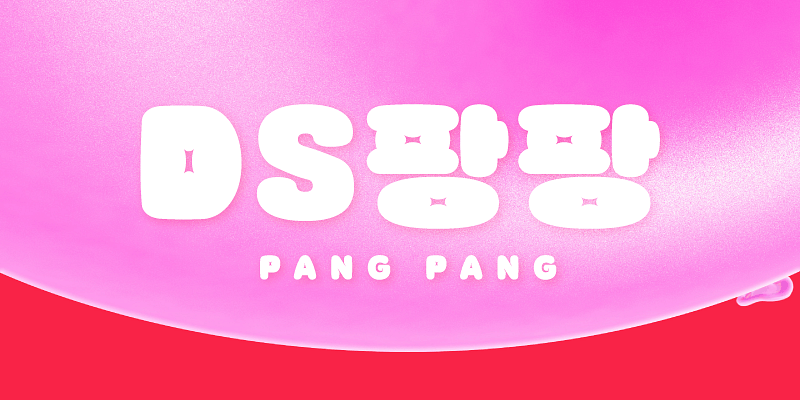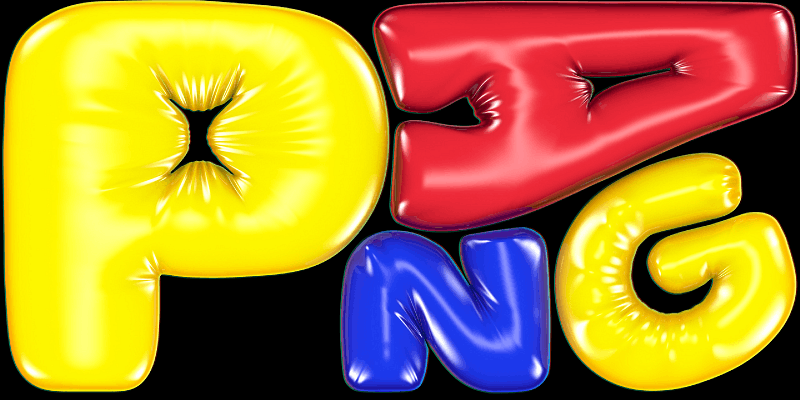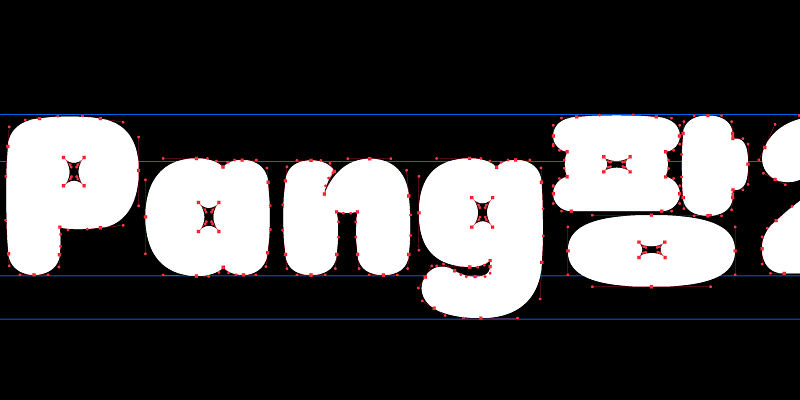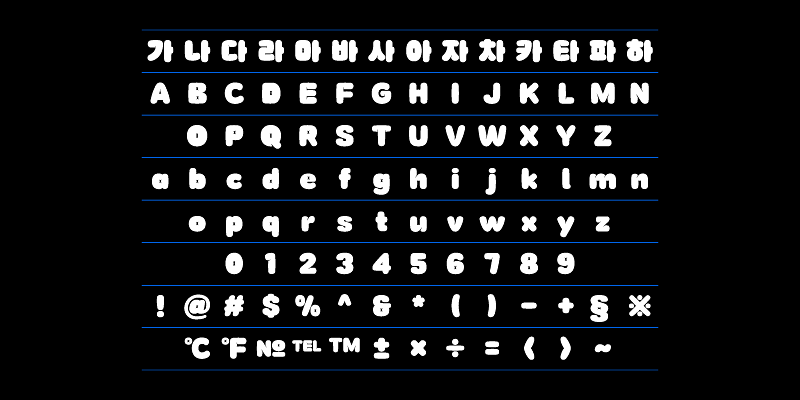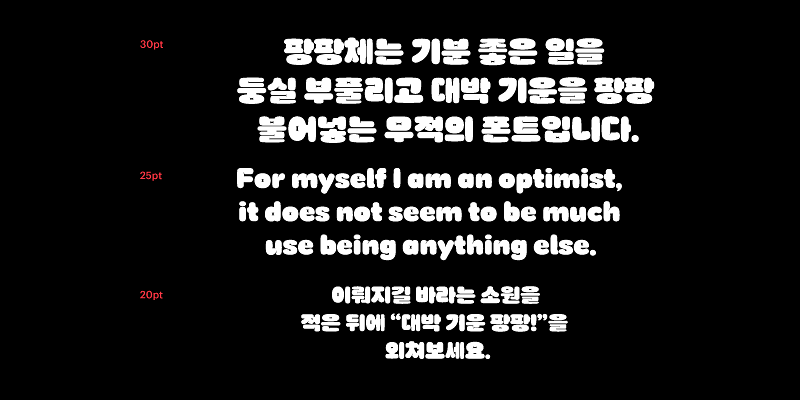
글꼴 페어링 가이드를 통해 자세한 내용 확인 >윤디자인그룹의 활기찬 디자인스튜디오 ‘엉뚱상상’이 선보이는 DS팡팡 폰트는 풍선처럼, 빵처럼 기분 좋은 일만 둥실 부풀리는 무적의 폰트입니다. 부드럽고 빵실빵실한 느낌을 주는 폰트로 친근하고 유쾌한 분위기를 가진 다양한 디자인 작업에 활용할 수 있습니다.